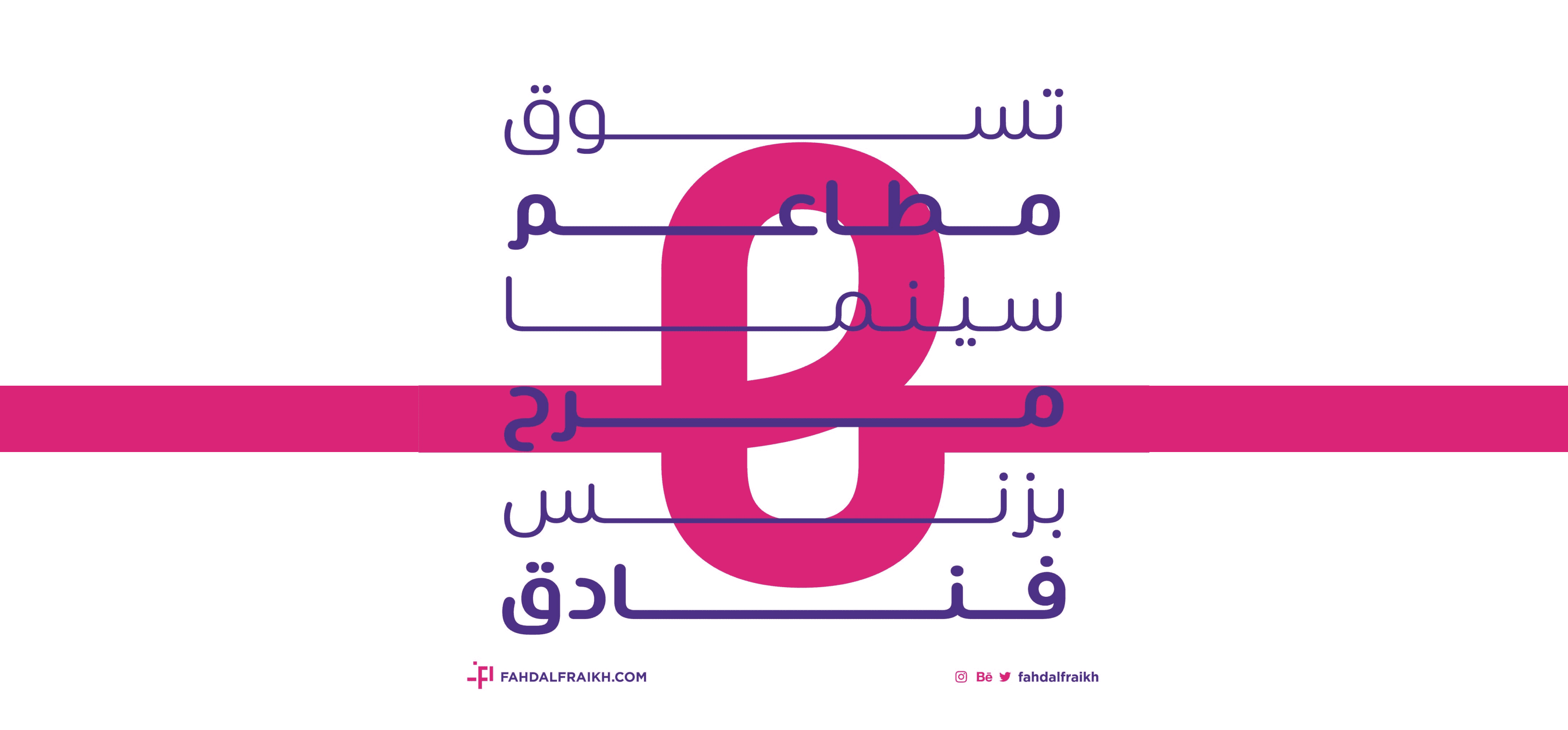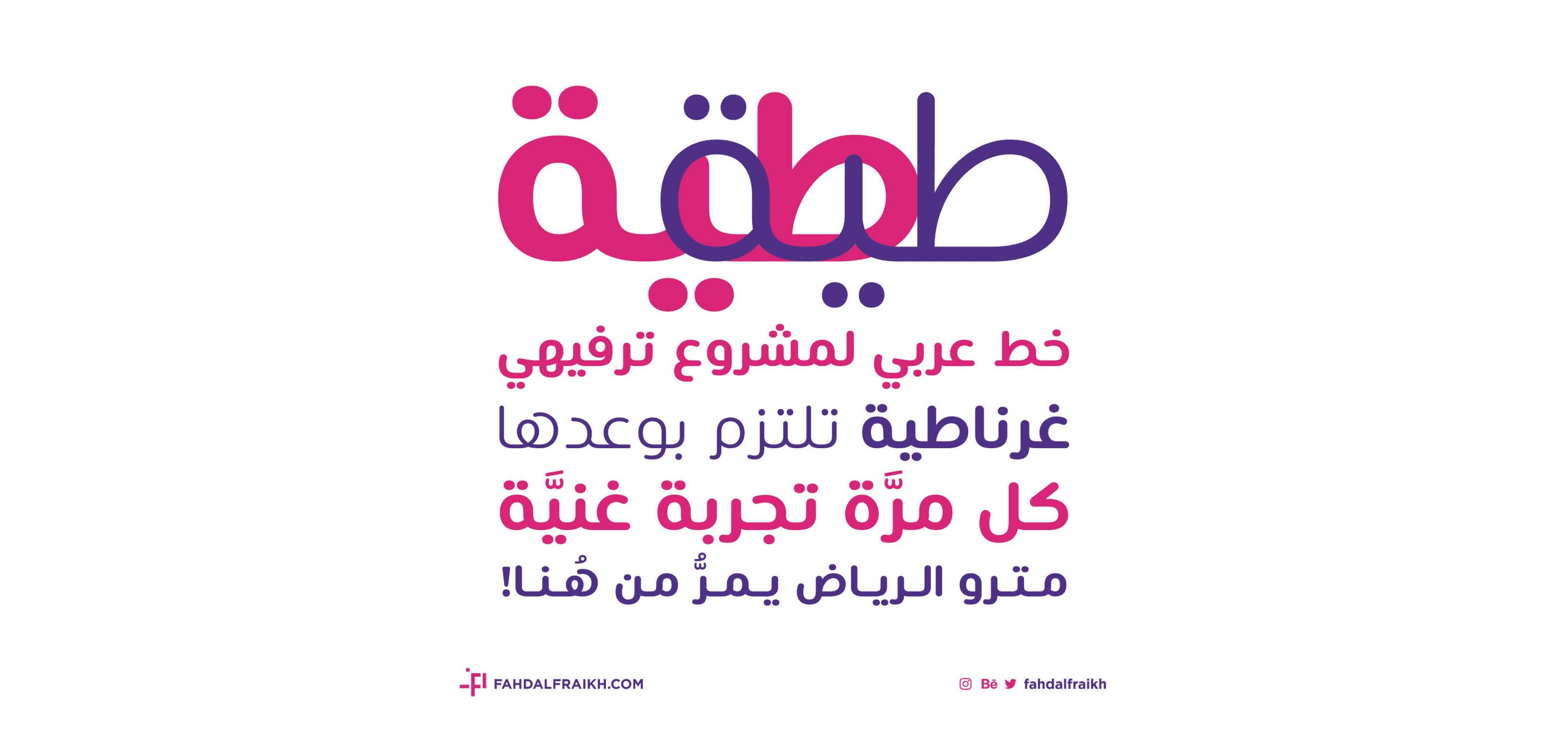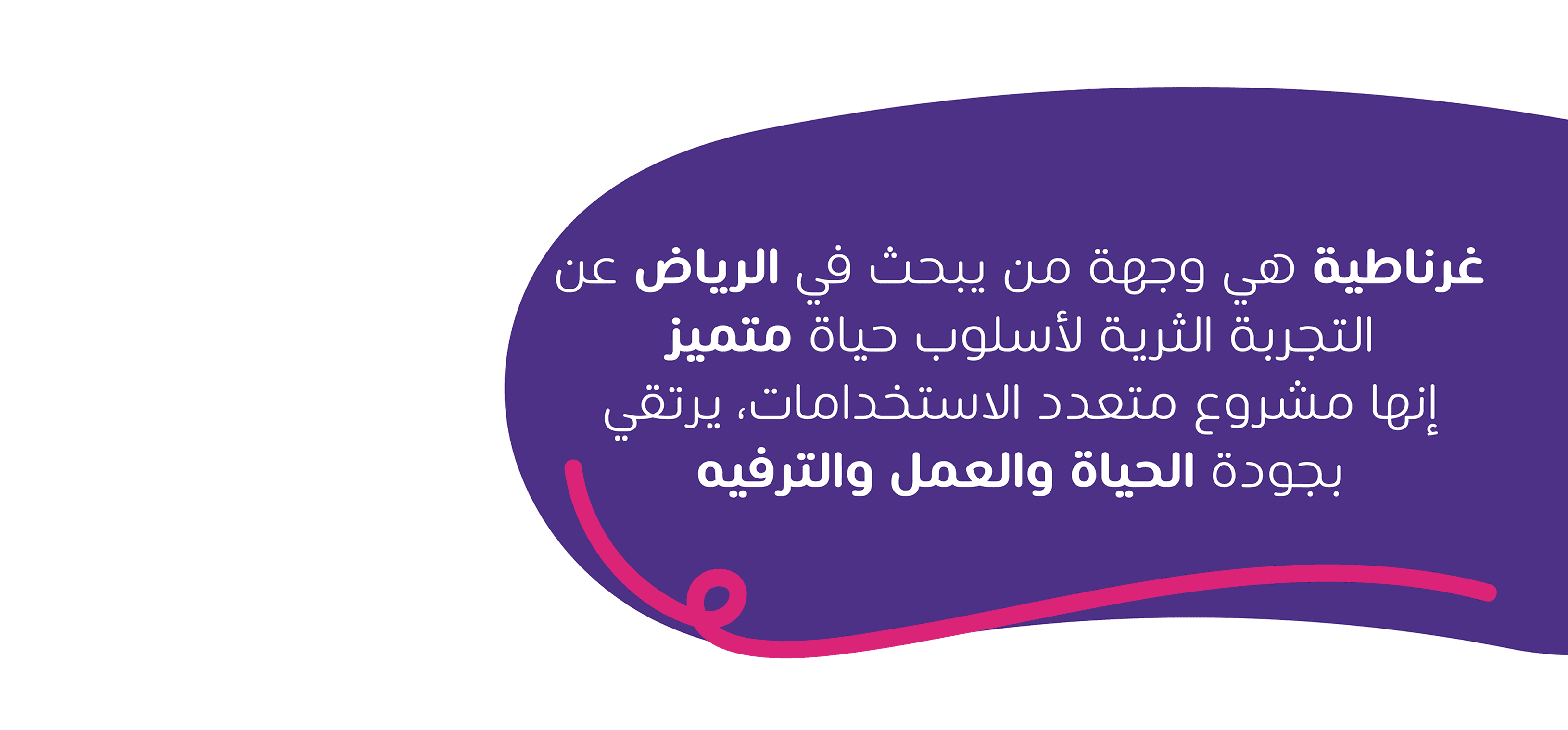
خط عربي ترفيهي بتصميم عصري ومبهج، صُمم خصيصًا لمشروع غرناطية الترفيهي ليكون جزءًا من هويته البصرية الرسمية.
يتميز الخط بانحناءاته الناعمة وتناسقه اللوني، مما يعزز من الإحساس بالمرح والطاقة الإيجابية.
يأتي الخط بوزنين (Book & Bold)، ويُعد مناسبًا للمشاريع التي تستهدف العائلات أو الأطفال، ويُستخدم في البيئات التفاعلية مثل المتاجر والمرافق الترفيهية.